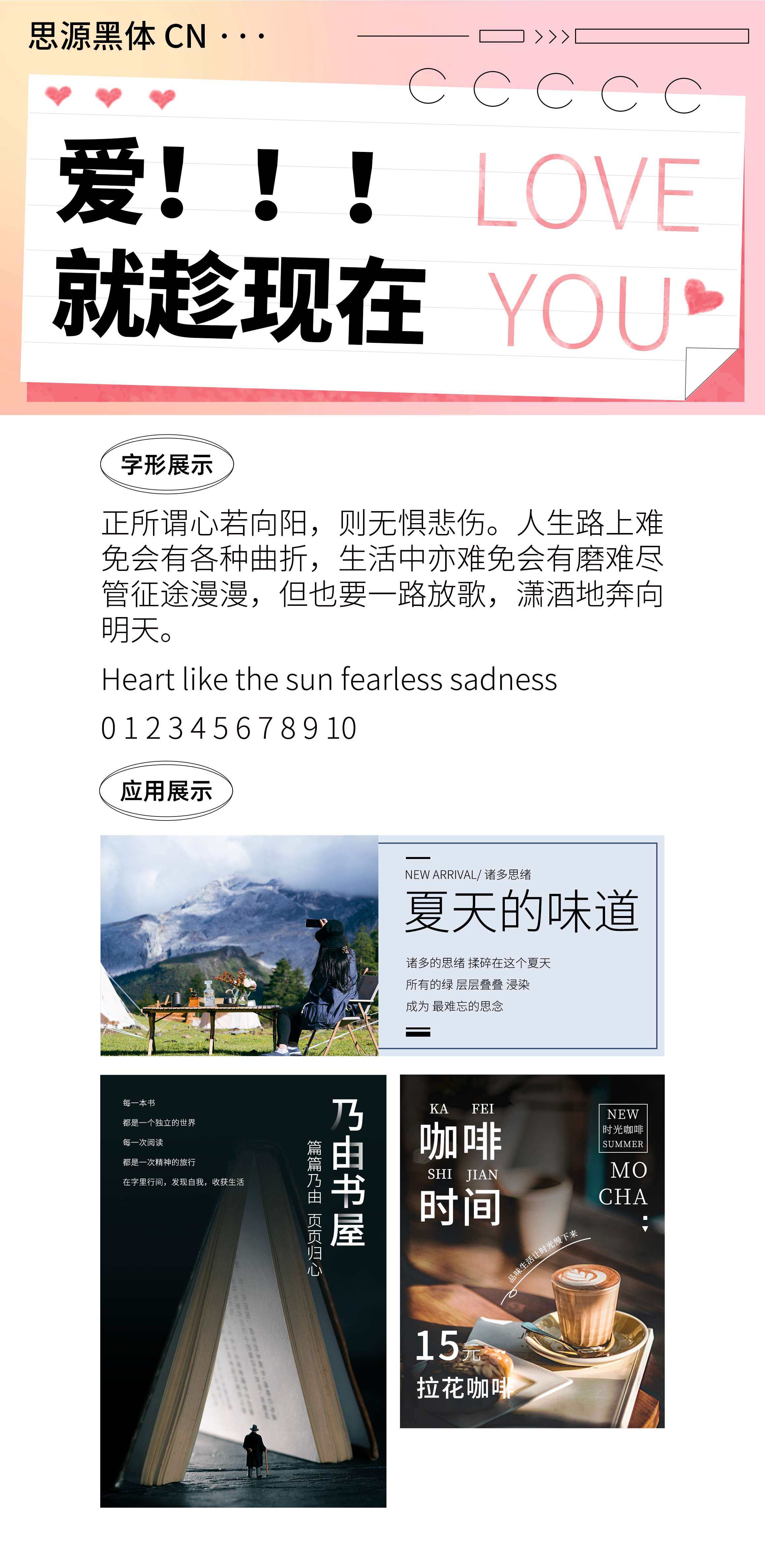
思源黑体
思源黑体是 Adobe 与 Google 合作推出的一款开源字体, 有七种字体粗细(ExtraLight、Light、Normal、Regular、Medium、Bold 和 Heavy),完全支持日文、韩文、繁体中文和简体中文,还包括来自 Source Sans 字体家族的拉丁文、希腊文和西里尔文字形共65536个字形。Google 将其命名为 Noto SansCJK,作为 Google 的 Noto 字体家族的成员。Adobe 则命名为 Source Han Sans,作为 Adobe 的 Source 字体家族的一员。Adobe 拥有字体设计的版权。发布的字体文件则可以不受限制的免费使用。